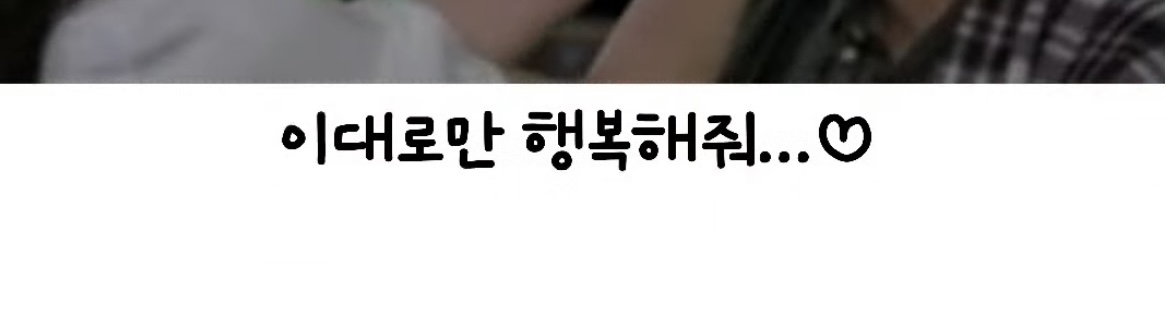
이 폰트 이름이 뭘까요 eun*** 2022.11.01 이 폰트 이름이 뭘까요 댓글 0 등록 Anun현주 음...획의 느낌이며 하트 모양을 봐서는 폰트가 아니고 손글씨인 거 같습니다..! 2022-11-03 답글 달기 댓글 더보기 쉽고 빠르게 가장 비슷한 폰트를 알고 싶다면? 이미지로 검색하기
음...획의 느낌이며 하트 모양을 봐서는 폰트가 아니고 손글씨인 거 같습니다..!